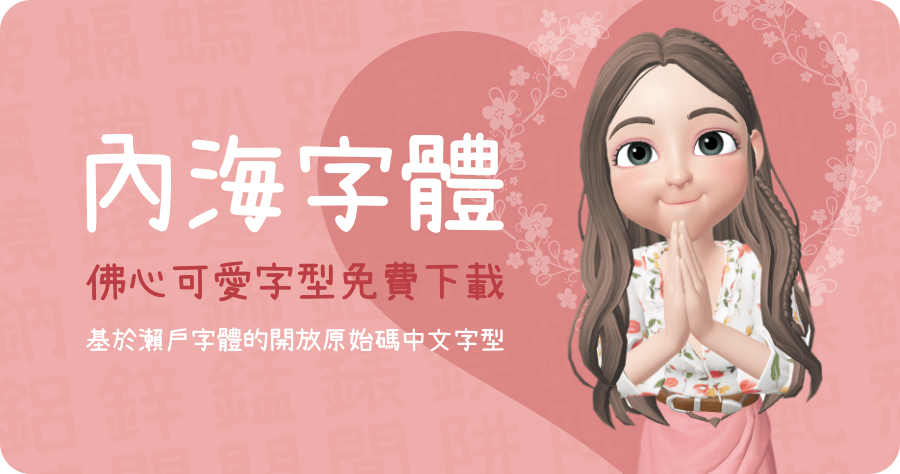
內海字體 NaikaiFont 基於瀨戶字體的開放原始碼中文字型免費下載
今日感到最佛心的事情,就是又多了「內海字體」這款可愛的繁體中文免費字型可以下載,這是基於「瀨戶字體」的開放原始碼中文字型,這真的是要好好感謝大神 Max 的努力,我們才有這麼可愛的字型可以下載使用,若以前你曾經使用過瀨戶字體,那麼多少會發現還是會有缺字的狀況發生,不過現在內海字體補足了這些缺字,而且還調整為 5 個字重,在全形標點符號上原本是針對日本做設計,調整成台灣的置中用法,還有加上了台灣閩南語常用字與部分粵語字,有沒覺得這真的很佛心啊~趕快來下載使用吧!
五種不同的字重:
「臺灣閩南語推薦用字 700 字表」中常出現的中文字,內海字體增加的 47 個字如下:㧒㧳㪗㾪䆀䉔䘼䩉䫀䫌螿蟧蟮蟳蠩覕譀趒趖跍跔跤踅踮蹛軁迌遢邋鐤雺頦骿魩鰇????????????????????????????????????????????????。這些自我用注音還不一定能打得出來啊~
增加部分的粵語字如下:㓤㖡㖭㖿㗎㗾㧬㨘㩒㬹㷫㹴䁪䢂䱽螆蠄裇覅趷踎踭蹾躀躝軚輋酶醖鈈鈪鎅鐧閪餸骾髧鮋鯭鰂